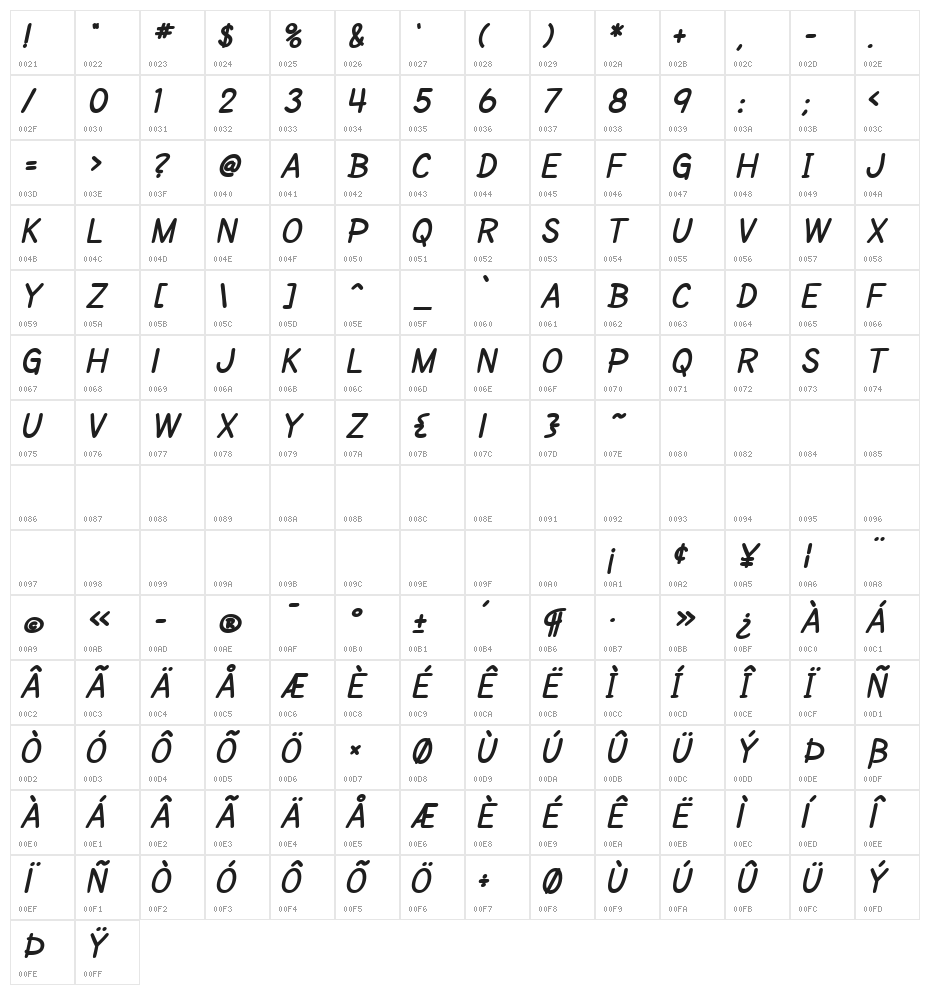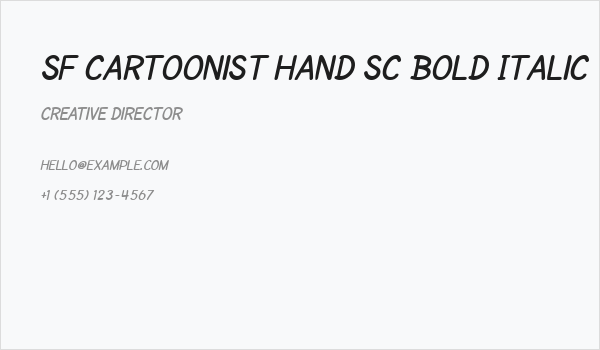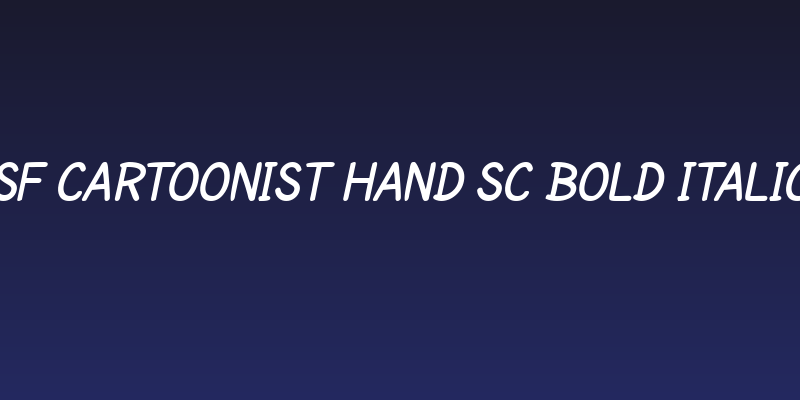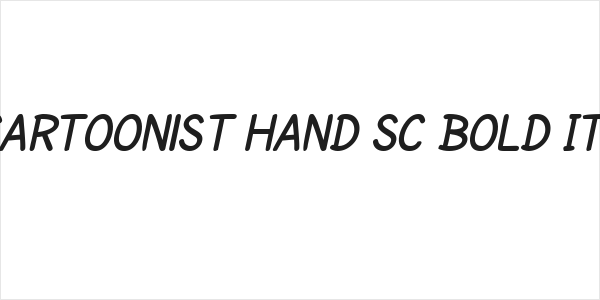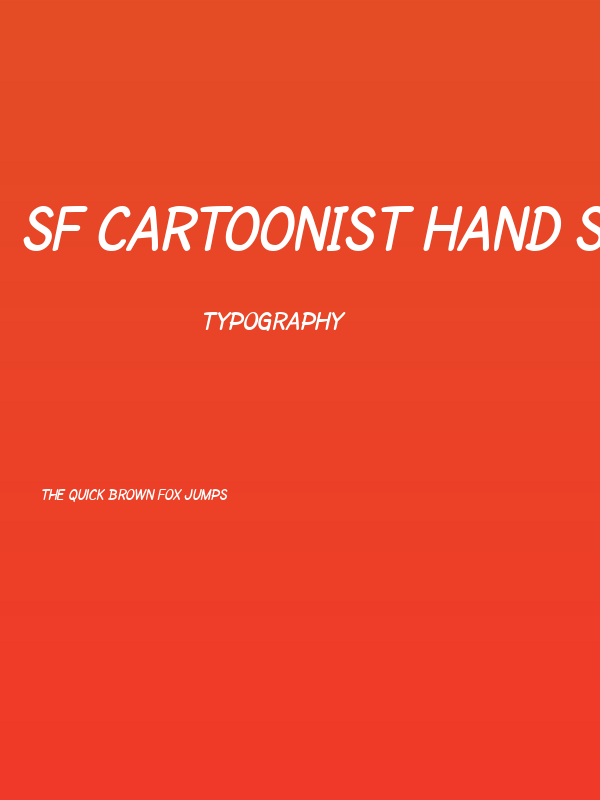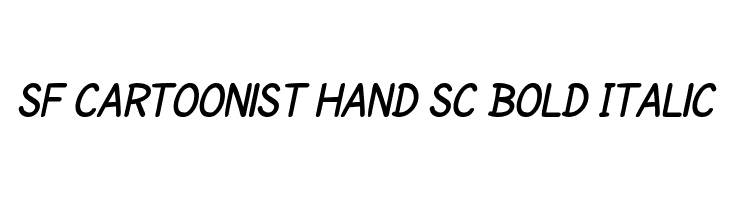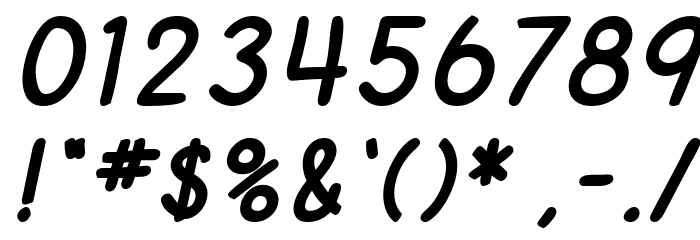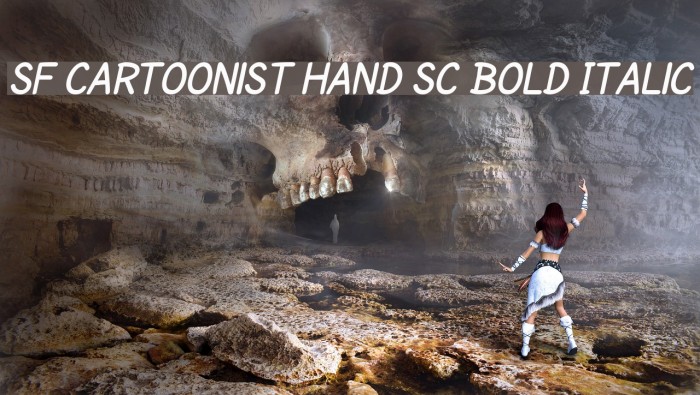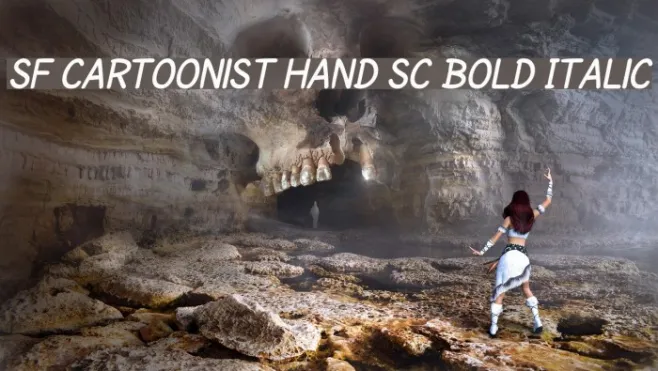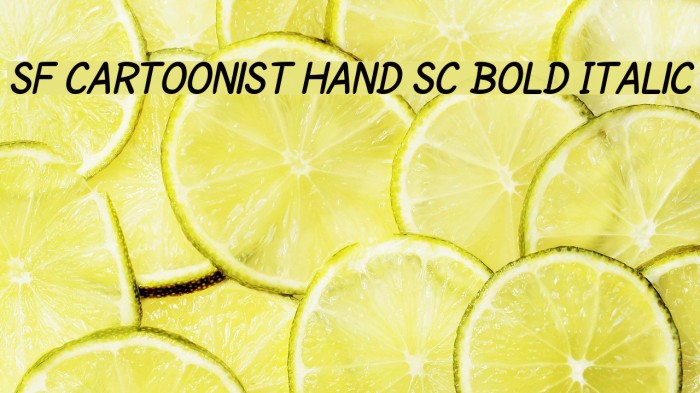
SF Cartoonist Hand SC Bold Italic Font
| Style général | Playful |
| Cas d'utilisation | Headlines, Logos, Informal Text |
| Projets proposés | Ideal for comic books, children's books, playful branding, greeting cards, and casual invitations. |